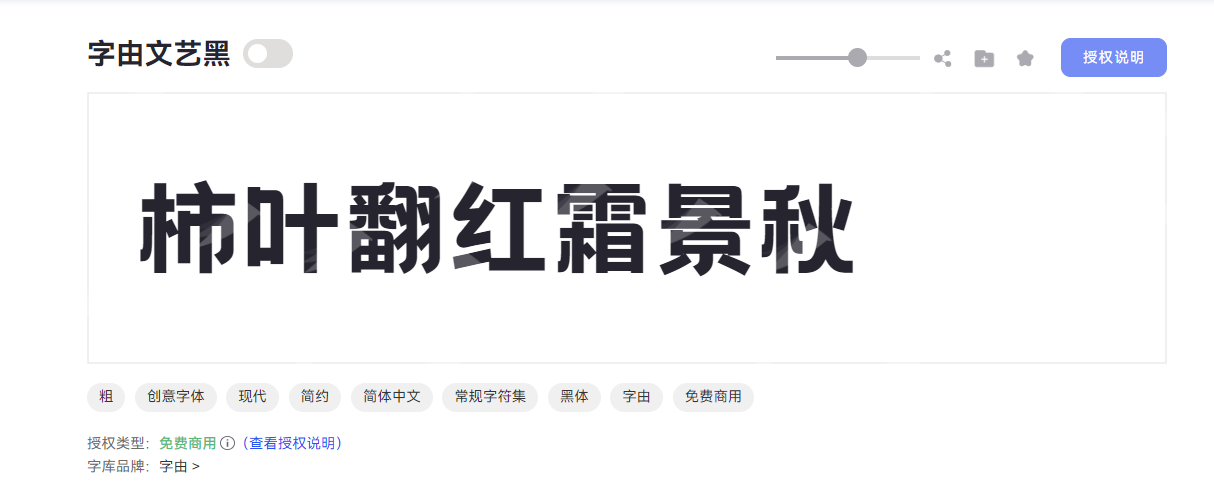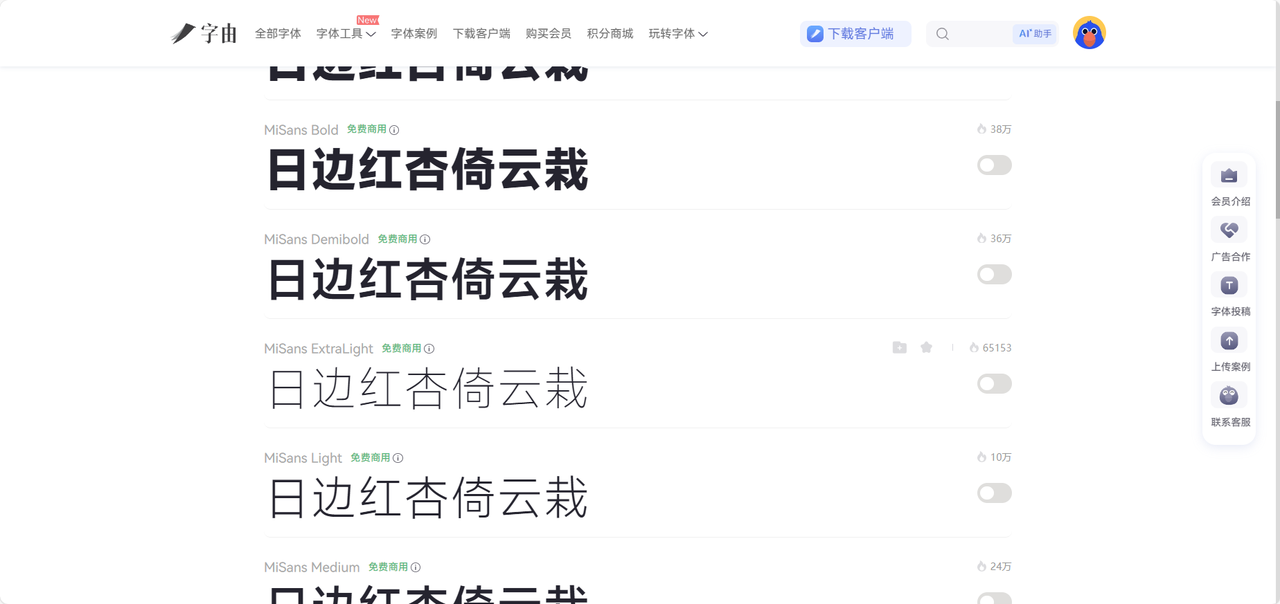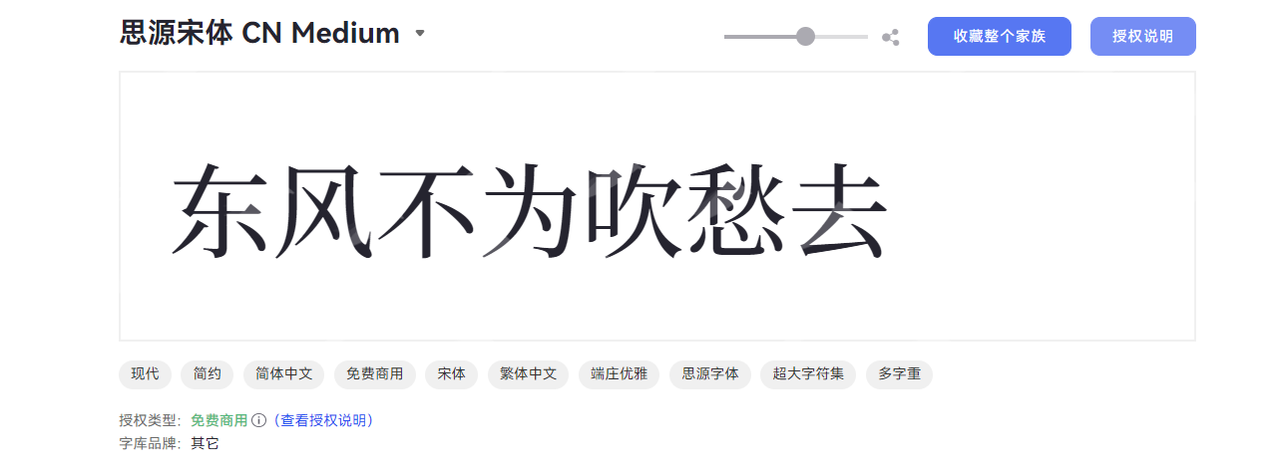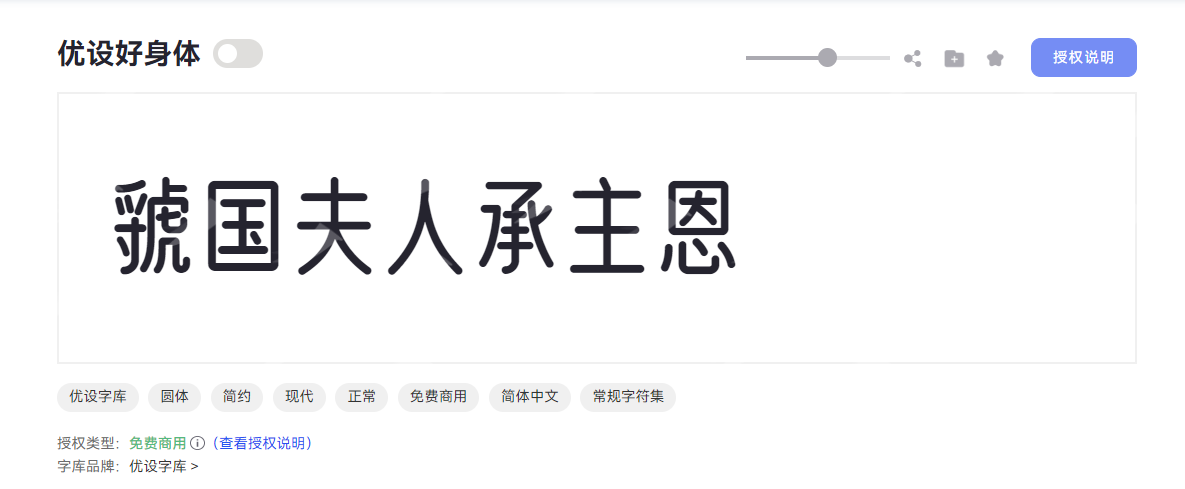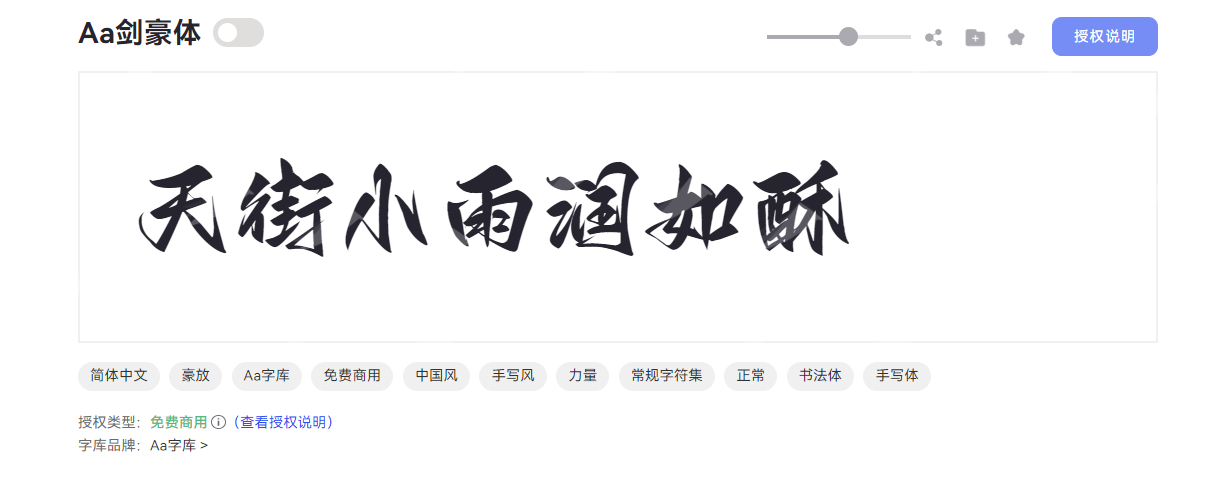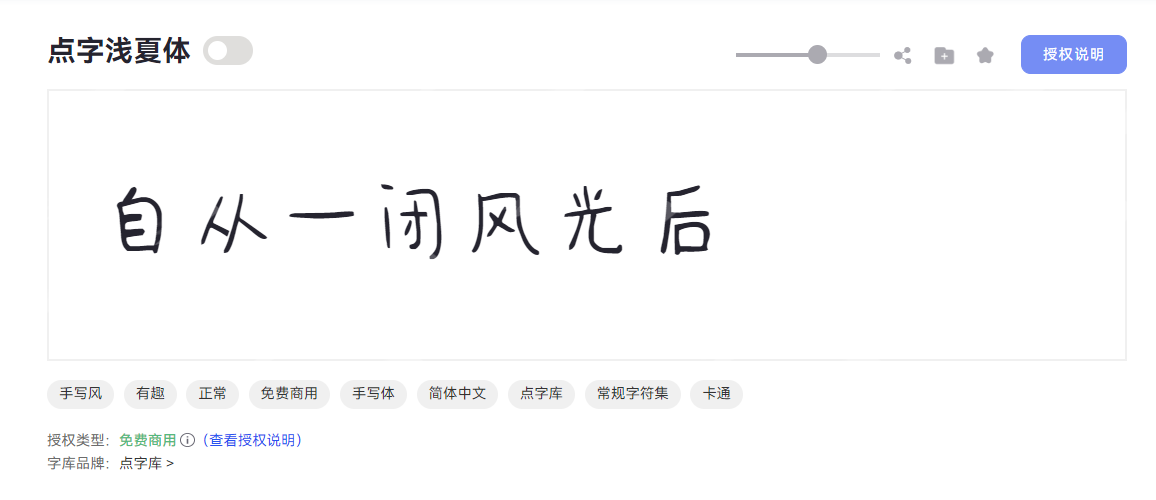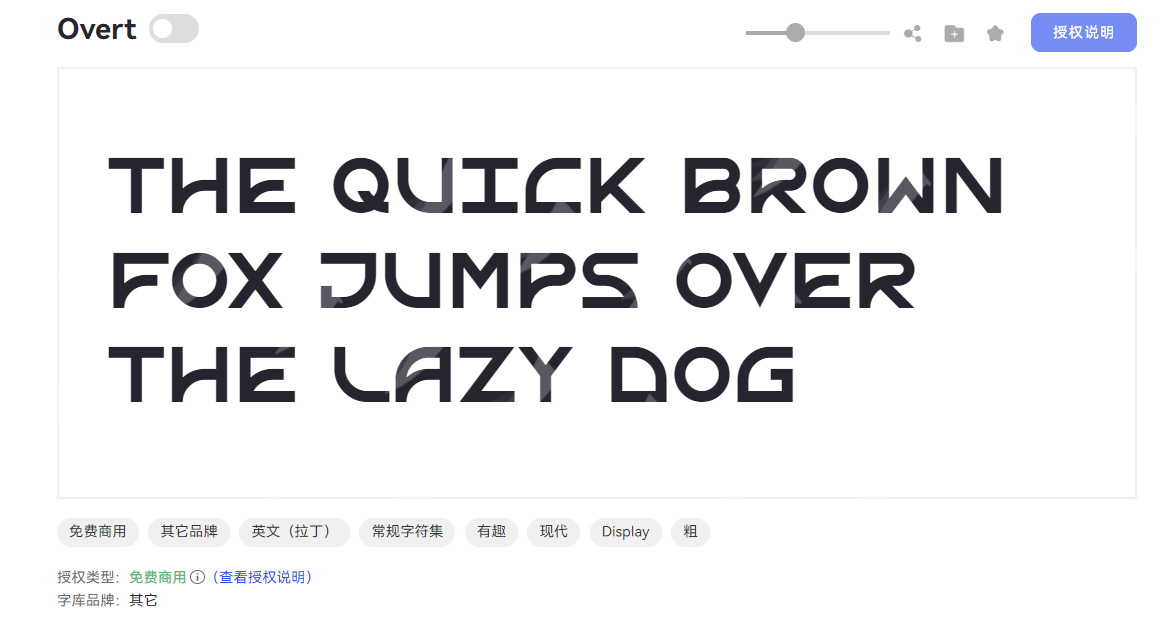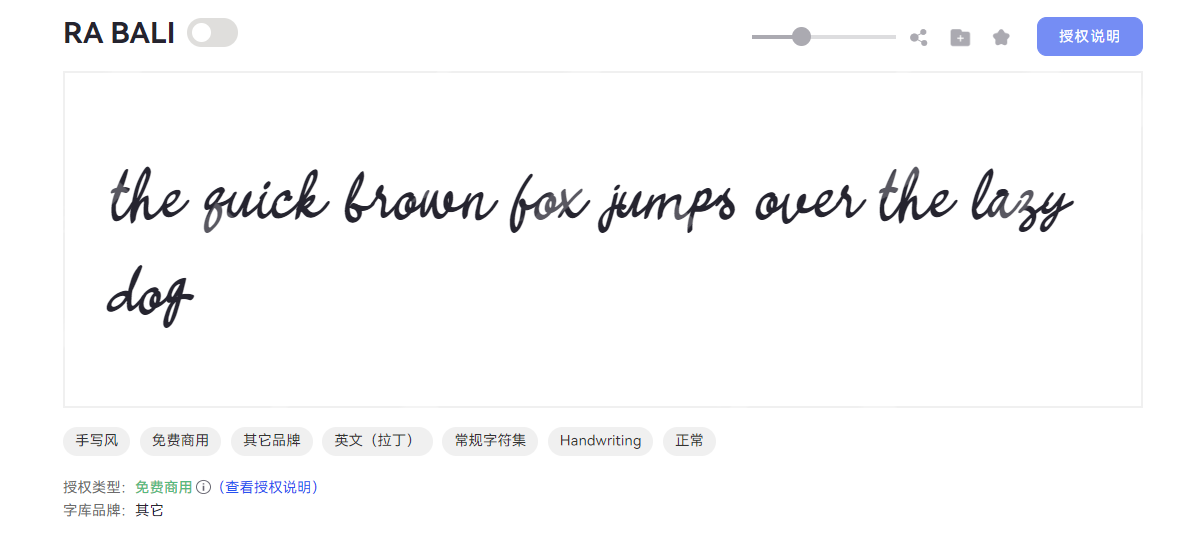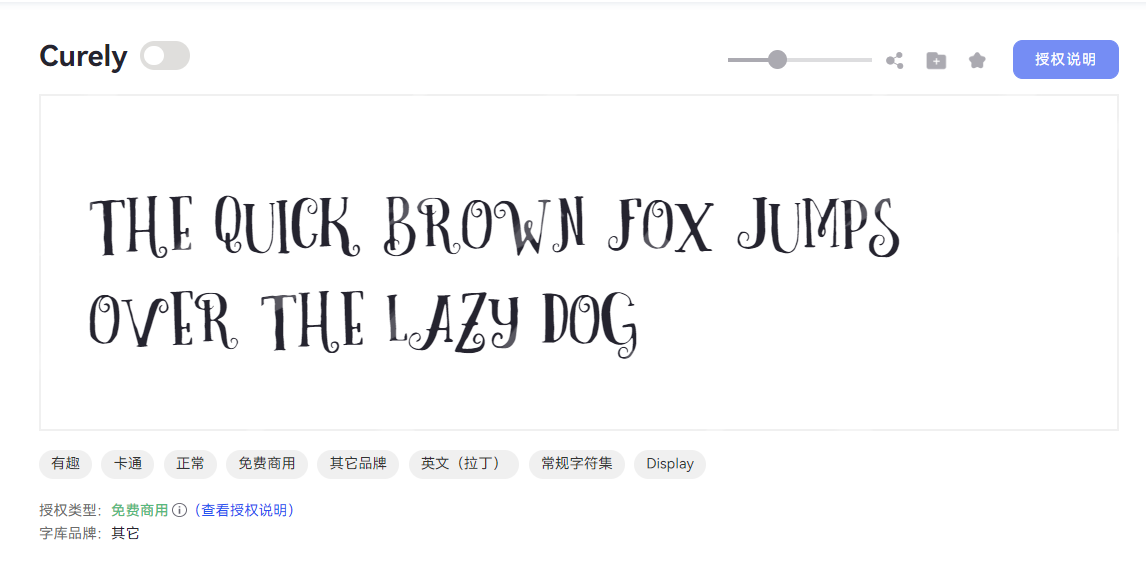
你是不是也经常在各大字体平台反复翻阅,苦恼怎么没有合适的免费字体,好不容易下载了自己满意的字体,还不小心涉及了侵权问题。一直以来,设计行业对版权问题的关注度都很高,想要精准找到免费可商用字体成为了设计师们的一大难题。这份2026年免费可商用字体大全,你可千万不能错过!接下来推荐的字体均是来自字由官网的正版字体资源,给大家整理出了使用率高、无侵权风险的优质字体。无论是品牌设计、海报设计等任何场景都可以放心下载哦。
一、免费可商用中文字体
1.字由文艺黑
字由文艺黑是字由品牌推出的创意黑体字体,深受设计师们的好评。该字体以现代简约风格为核心,字体字形方正饱满,重心居中,保留了黑体原本的稳重感,艺术弧线的设计又增强了视觉张力,使得字体呈现出来更加生动。作为免费可商用字体,它更适用于海报设计、品牌视觉、新媒体排版等多元场景,兼顾艺术性与实用性,是现代设计中追求文艺感与商业价值的理想选择。
2.MiSans 字体
MiSans 是一款现代简约风格的黑体字库,以超粗字重与利落设计为核心特色,而且它总共包含 10 款字体,你可以根据需求自行选择。字形结构方正稳重,相比于上一个字体,MiSans 字体的笔型采用直角设计,搭配方头笔画形态,利落的笔触增强了现代感,比较适合用于正式庄重的场合。除此之外,它的笔型平直有力,简约的设计有效减少了视觉负担,尤其适配屏幕显示场景,这款字体在手机、电脑等设备上均能清晰呈现,使用者阅读体验感会大幅提升。
3.思源宋体
思源宋体是由谷歌与 Adobe 联合打造的开源现代宋体字体,支持个人及商业项目免费商用,涵盖28款不同类型的字体选择。作为排版领域的实用选择,思源宋体以端庄优雅的设计风格而闻名,字形方正稳重,重心居中,既保留宋体传统韵味,又注入现代设计基因。支持简繁中文及超大字符集,多字重设计满足从正文到标题的多样排版需求,无论是书籍内文、网页界面还是品牌文案,均能呈现清晰易读的视觉效果。
4.优设好身体
优设好身体是优设字库联合字由发布的第二款免费商用圆体字体,整体风格偏简约,授权范围覆盖全场景免费商用,满足个人与企业的多样化设计需求。优设好身体保持了圆体的柔和特质,又通过方正结构增强了视觉稳定性。字体在笔型设计上融入细腻圆角处理,笔画粗细均匀且呈圆头形态,整体观感圆润亲和,打破传统圆体的臃肿感,传递轻松友好又带有一丝俏皮的设计氛围,是现代设计中兼具实用性与美感的优质免费商用字体选择。
5.剑豪体
剑豪体是 Aa 字库推出的一款中国风手写体,它将统书法韵味与现代设计需求巧妙融合,用在古风类的设计作品中再合适不过了!剑豪体给人的视觉体验以“力量”和“豪放”为主,中宫收紧的结构让字体在紧凑中透出张力,宛如剑刃出鞘般利落,透露出一种江湖气息。最值得一提的是,它的笔型融入利落斜切,笔画断连分明的处理透出剑势般的刚劲以及手写体的随性。无论是在武侠类的主体海报、古风文创类设计等场景,剑豪体能轻松准确传递出豪迈洒脱的东方韵味,打造出具有文化底蕴的设计作品。
6.点字浅夏体
点字浅夏体经常被用于儿童类的主体海报、夏日社交媒体配字、趣味标题设计等领域,因为它独特的手写风格,可以让人一秒感受到夏日的清新与灵动。它是一款充满手写温度的卡通手写体,字体整体字形方正有度。我最喜欢的是笔型设计,圆角勾勒的笔画搭配圆头收尾,让每个字符都像被阳光吻过的气泡,轻盈又可爱。而且点字浅夏体的笔画不是完全链接到一起的,打破了传统书写体的连贯性,反而会让人觉得活泼俏皮。
二、免费可商用英文字体
1.Overt
Overt 是一款专为英文设计的现代 Display 字体,适合作为标题或视觉焦点文字,轻松吸引观者目光。它的笔画富有力量感与细腻的表达,如果用于品牌设计、创意海报标题,会给你的创意加很多分,提升作品的记忆点。Overt 是粗重字体,更偏向于有趣且现代的风格,支持免费商用授权。字形修长利落,重心偏高的设计赋予字体向上的轻盈张力,中宫适中的比例则平衡了视觉节奏,让整体形态既保持现代感又不显局促。
2.RA BALI
RA BALI 是一款极具个性的英文手写风字体,以独特的设计细节和随性的自然风脱颖而出。该字体在笔型设计上暗藏巧思,融入独特斜切工艺,搭配圆润饱满的笔画端头,让每一笔都兼具利落锋芒与柔和质感。 值得一提的是,RA BALI 的笔画采用断开式连接设计,既还原了手写时自然的停顿与呼吸感,又避免了连笔字体可能带来的阅读干扰,让文字排布更显通透清爽。
3.Curely
Curely 是一款充满趣味的英文 Display 字体,以卡通风格为核心设计理念,适用于各类创意设计场景,尤其适合卡通标题、动画封面等,最近涉猎这些领域的设计师们一定要收藏这个字体哦。Curely 会在一些意想不到的地方对该字母进行笔画的延伸,既能轻松看懂字母,又可以呈现出活泼有趣的感觉,而且能在标题设计中形成独特的视觉焦点。它的笔画采用纤细均匀的线条,搭配个性鲜明的斜切装饰元素,尖锋笔画与断开式连接设计形成巧妙对比,帮助你轻松打造活泼有趣的视觉作品。